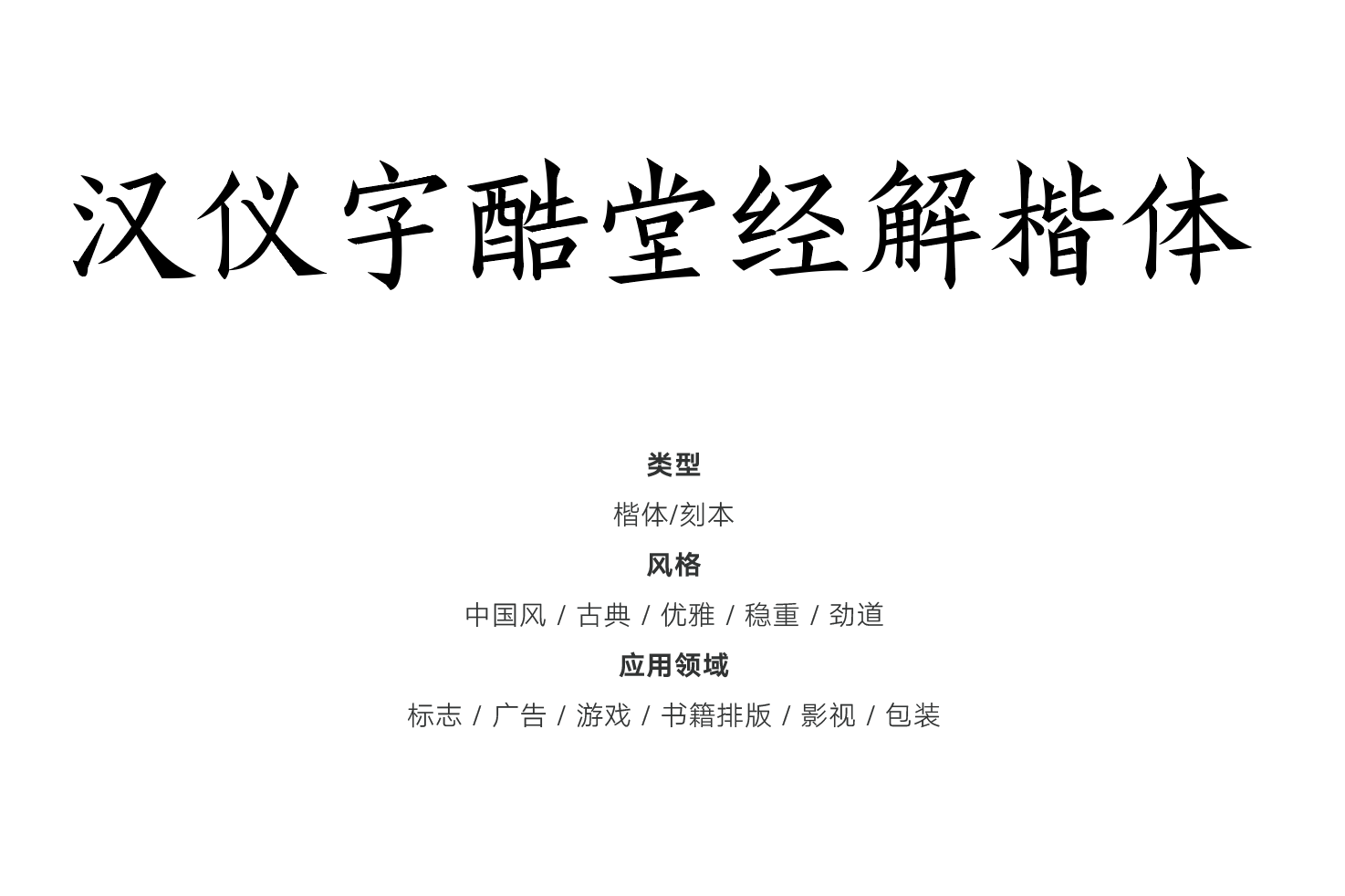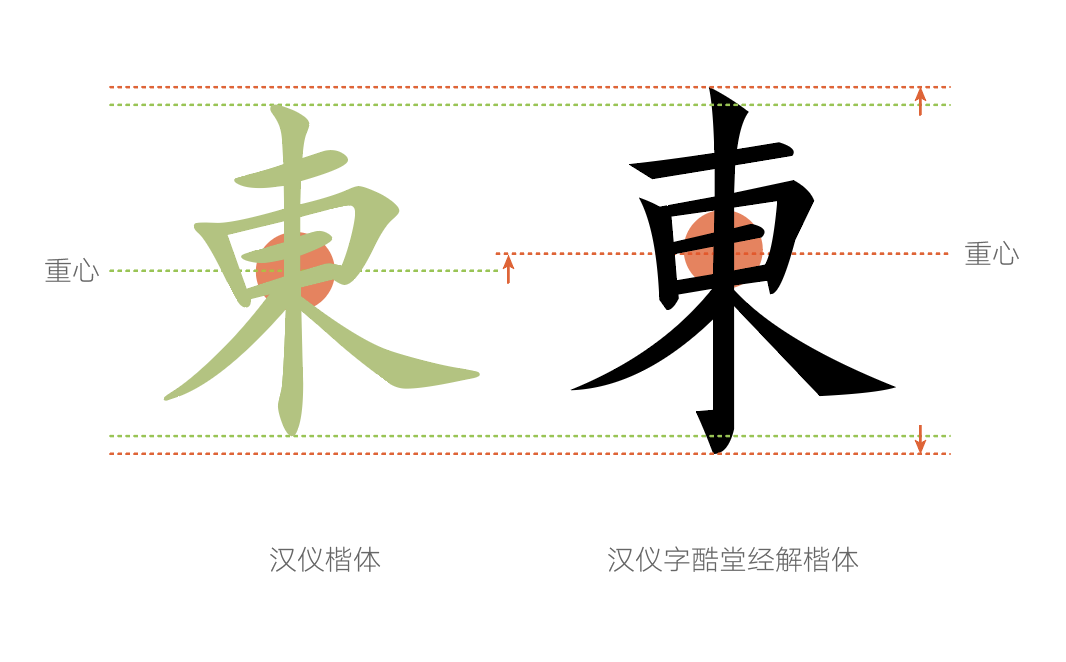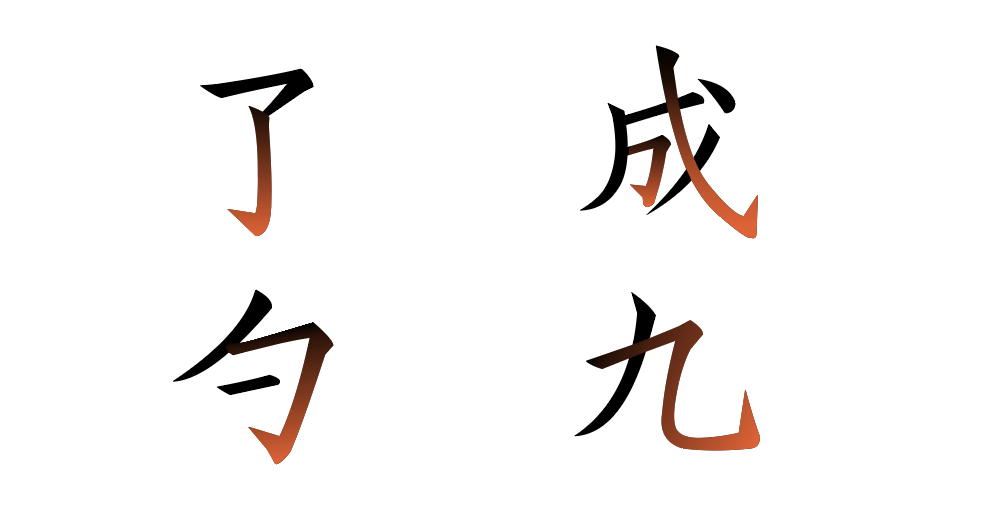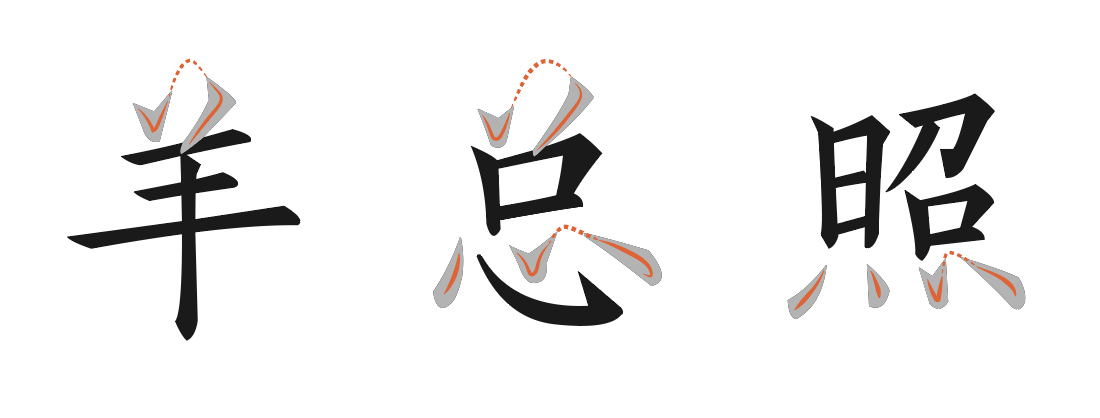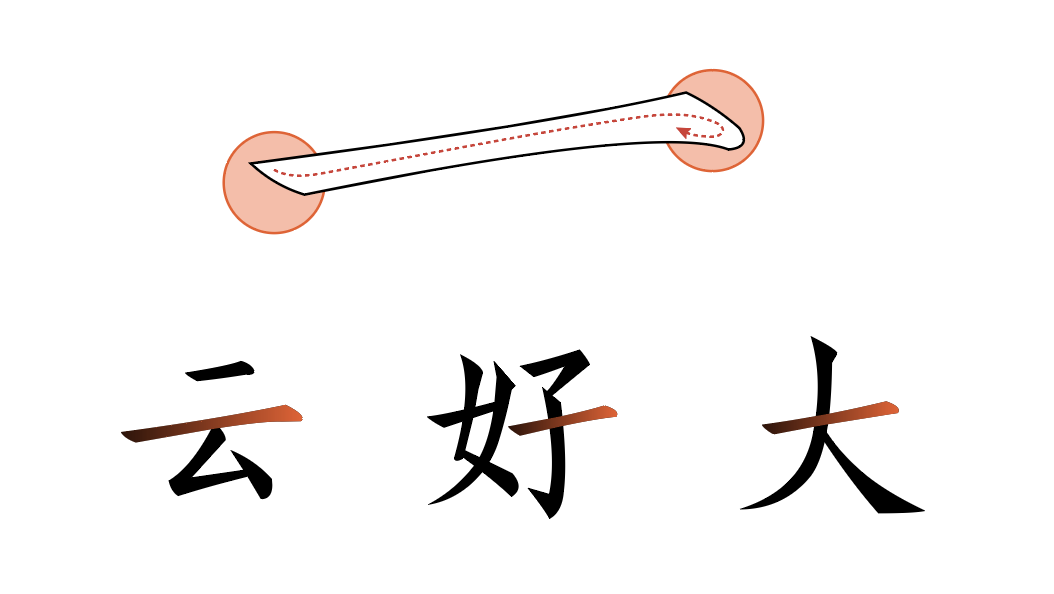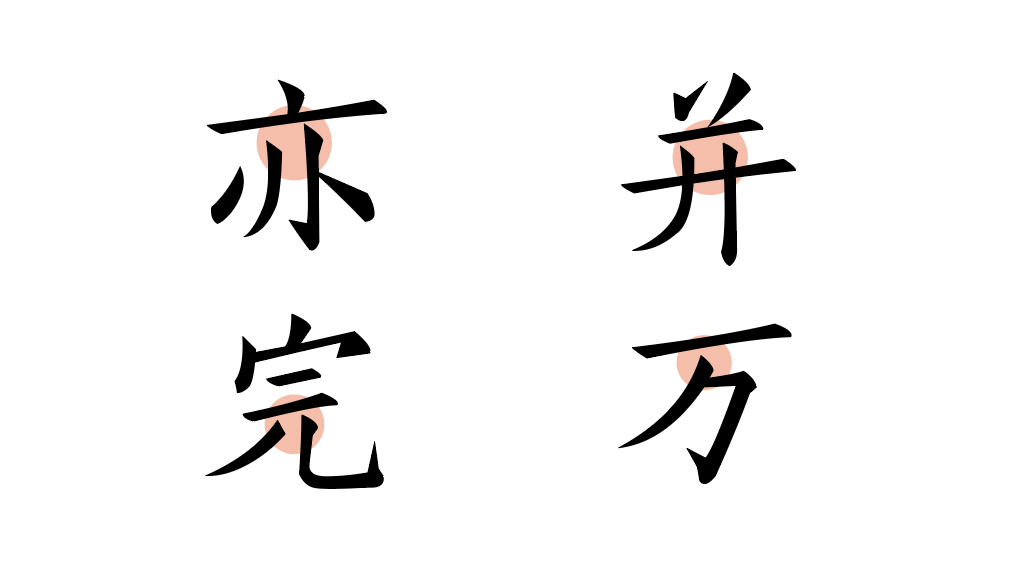
字體來源
漢儀字酷堂經(jīng)解楷體來源于古籍《通志堂經(jīng)解·經(jīng)典釋文》一書(清康熙年間,陸德明撰),字體有歐體楷書風(fēng)格,嚴(yán)謹(jǐn)工整、平正峭勁。
漢儀字酷堂經(jīng)解楷體作為一款復(fù)刻字體,保持了原刻本筆畫堅(jiān)挺,骨氣內(nèi)含,既不過分瘦勁,又不過分豐滿的風(fēng)格特點(diǎn),在貼近刻本原貌的同時(shí),還十分注重字符的易讀性和辨識(shí)性。
字形修長,嚴(yán)謹(jǐn)工整
相對于常見楷體(漢儀楷體)而言,漢儀字酷堂經(jīng)解楷體在縱向上的拉長延伸使得字體在縱勢上顯得疏朗、修長、剛勁、挺拔。
筆畫出鋒勁健,遒勁有力
漢儀字酷堂經(jīng)解楷體的筆畫方圓兼施,以方為主。橫畫左低右高,露鋒入筆,筆鋒尖銳,中部飽滿,收筆內(nèi)斂,形成一個(gè)圓弧頭。
漢儀字酷堂經(jīng)解楷體的點(diǎn)畫飽滿,活潑靈巧,筆勢連貫,點(diǎn)畫之間形斷意連,相互呼應(yīng)。 漢儀字酷堂經(jīng)解楷體的鉤畫像等腰三角形一樣,勁挺銳利,有“鐵畫銀鉤”之稱。 漢儀字酷堂經(jīng)解楷體為了使字體更有呼吸感,氣息更加流暢,在部分上下結(jié)構(gòu)漢字的筆畫銜接處做了留白處理。
貼近刻本原貌
漢儀字酷堂經(jīng)解楷體遵從了傳統(tǒng)的書寫方式,使其在布白均衡且易識(shí)別的前提下,最大程度還原了刻本的原貌。